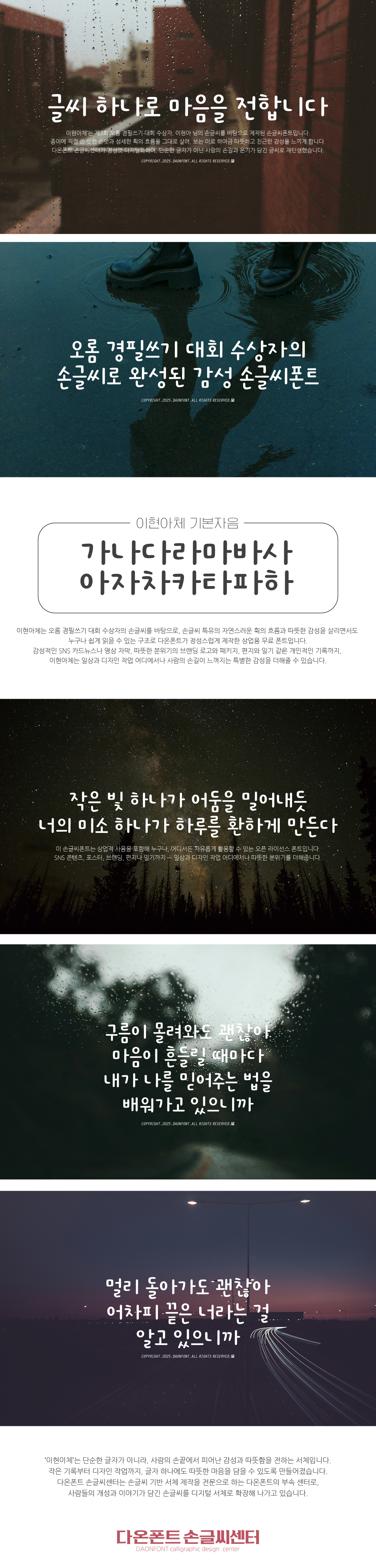
오롬 경필쓰기 대회 두번째 수상작, '이현아체'가 무료 배포 시작!
오롬 경필쓰기 대회의 두 번째 수상자인 이현아 님의 손글씨를 바탕으로 제작된
'이현아체'가 2025년 7월 30일 무료로 배포됩니다!
‘이현아체’는 손글씨 특유의 자연스러운 획의 흐름과 따뜻한 감성을 살리면서도
누구나 쉽게 읽을 수 있는 구조로 다온폰트가 정성스럽게 제작한 상업용 무료 폰트이며,
이현아님의 손글씨에 담긴 정성과 따뜻함을
여러분의 디자인과 글 속에 담아보세요.